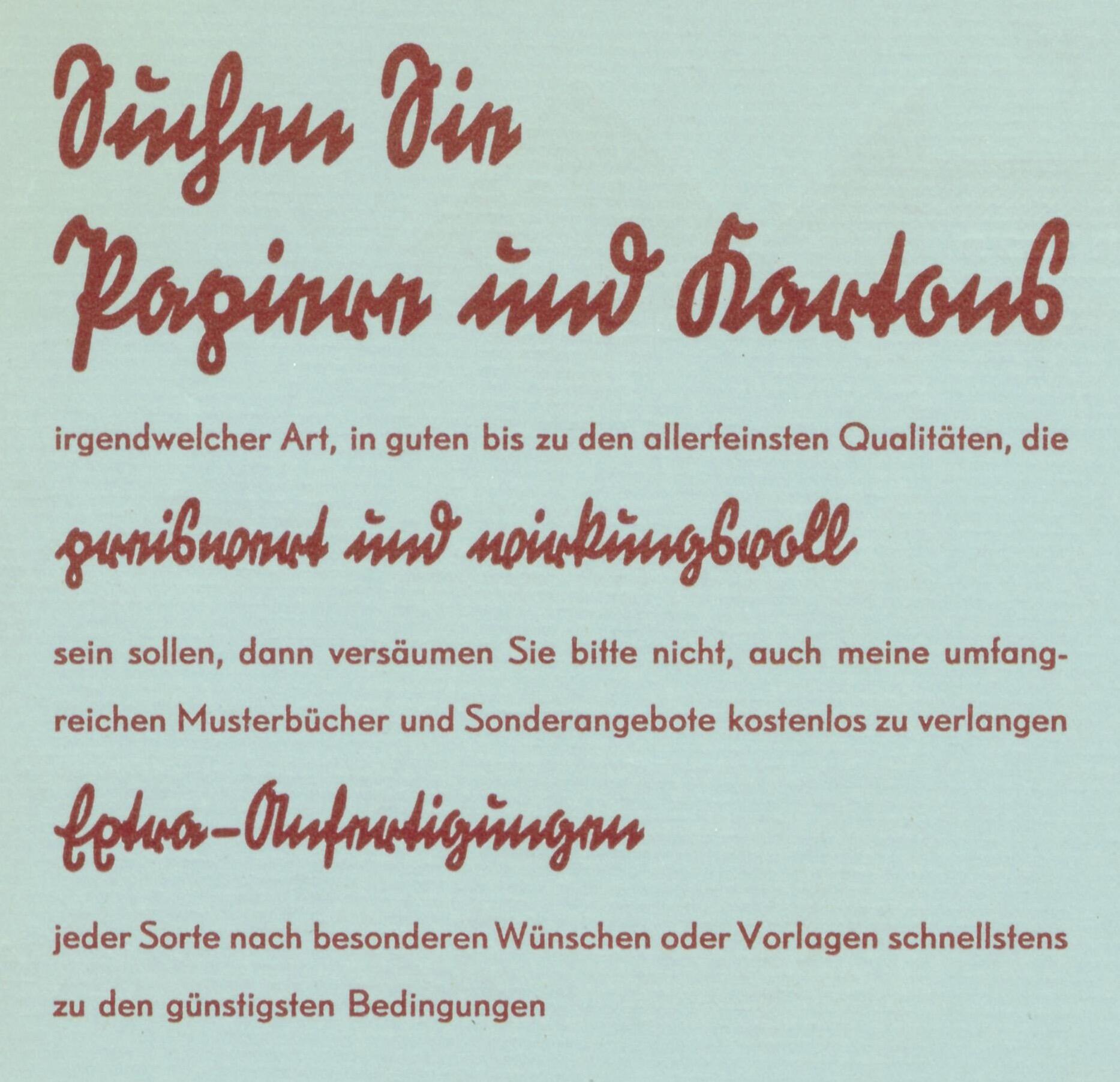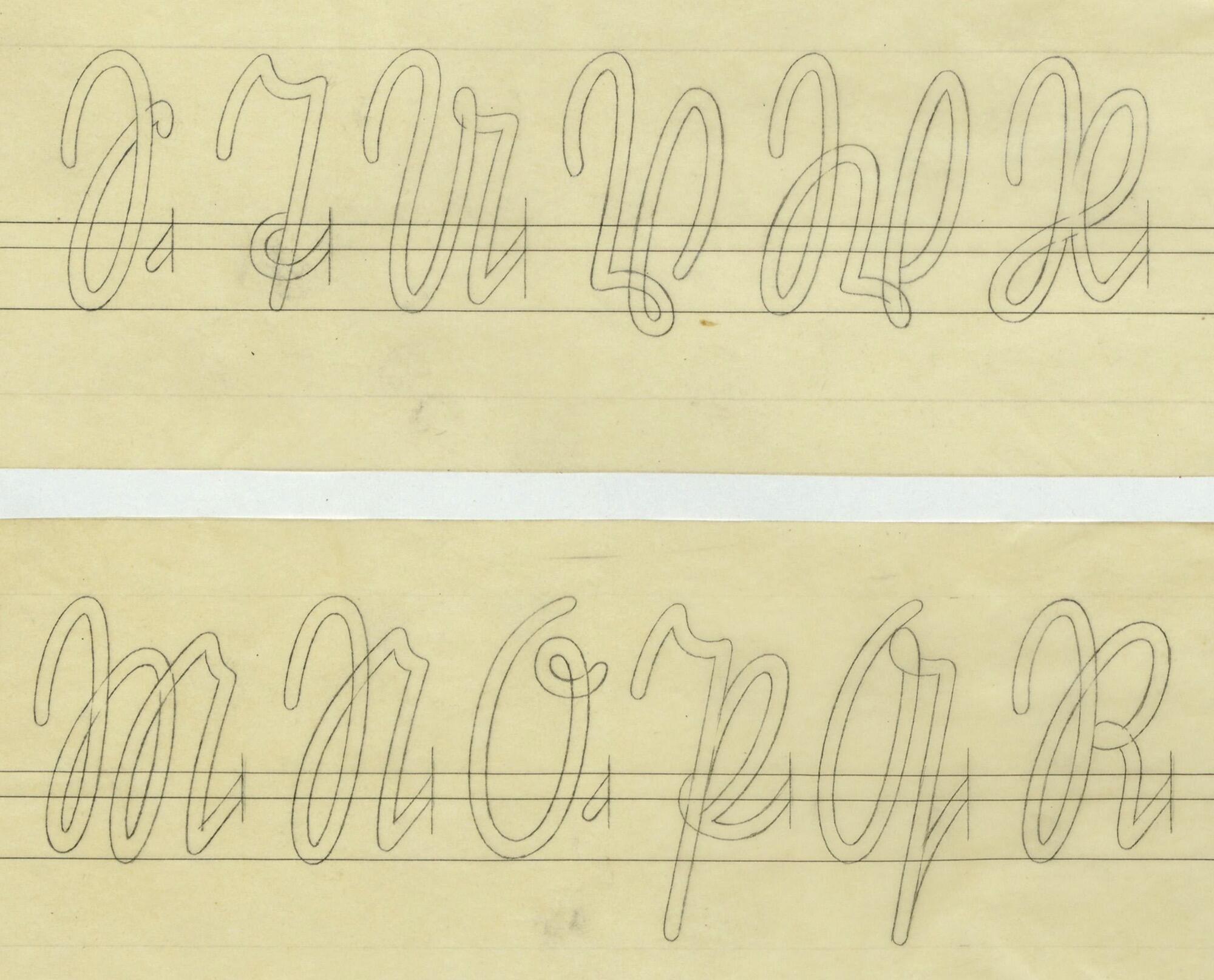
Font-Wiki: Deutsch-Signal
• 1934
• Gebrochene Schrift
Die Deutsch-Signal von Walter Wege ist eine Erweiterung der Signal-Familie um einen Schnitt im Stil einer Kurrent-Werbeschreibschrift der Zeit. Die Original-Unterlagen zeigen zunächst den Namen Sturm-Signal. Die Schrift erschien letztlich jedoch 1934 als Deutsch-Signal.